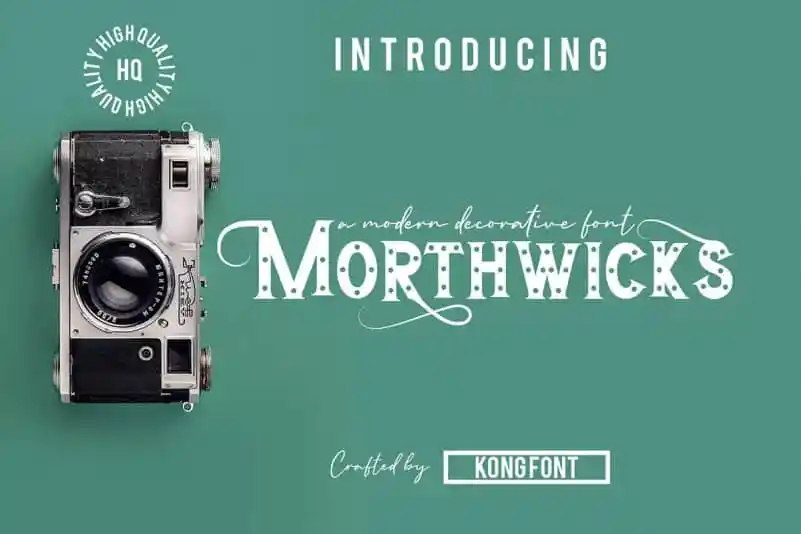
Morthwicks Display Font – Download Grátis
Se você está à procura de uma fonte tipográfica serifada para uso em rótulos, capas ou postais, então provavelmente esta é a escolha certa. Morthwicks é um tipo multilíngue que combina escrita a mão com recursos digitais da fontkong. Possui letras maiúsculas e números em todas as proporções, bem como sinais de pontuação, tornando-o perfeito para escrever inscrições nos rótulos ou embalagens das criações criativas mais atrativas. Este tipo personalizado é ideal tanto para designers que desejam adicionar uma textura a seus projetos quanto para quem busca um visual elegante e sofisticado em suas identidades de marca. Morthwicks está aqui para tornar seu próximo projeto de design uma realidade, seja ele um rótulo de produto criativo ou um anúncio publicitário impecável.